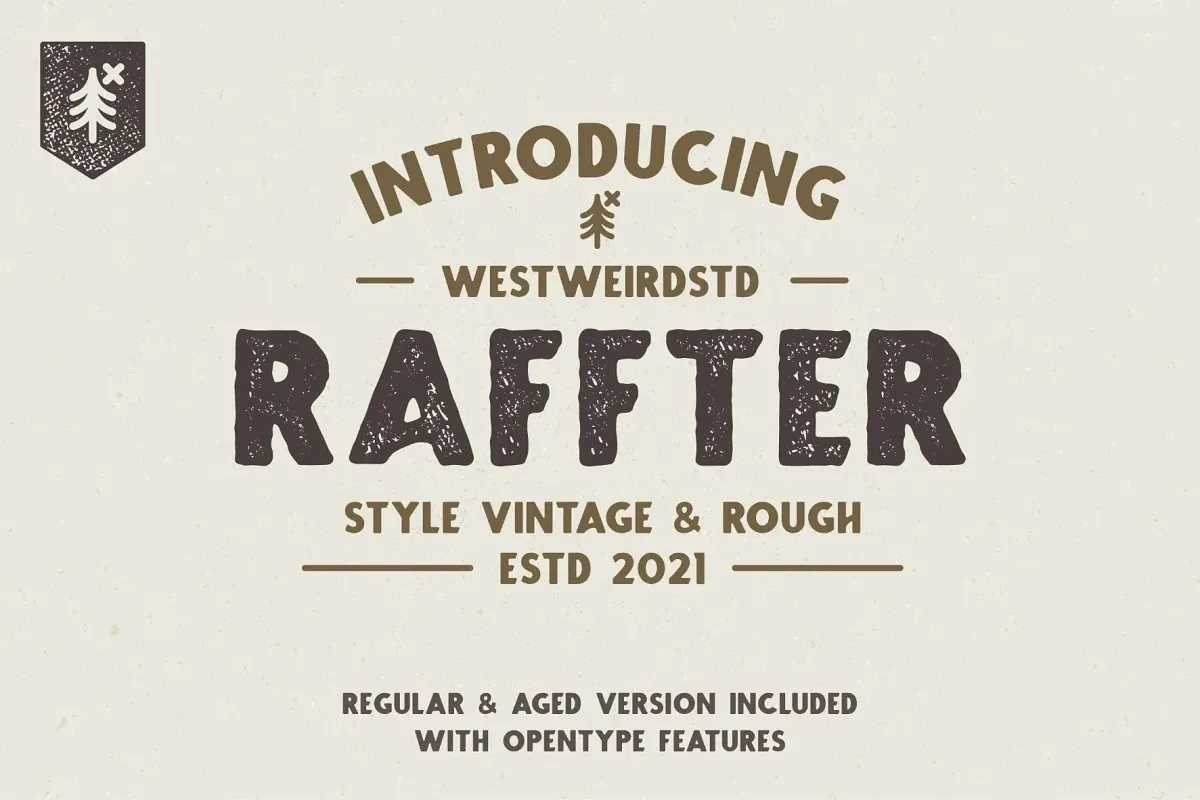
A Raffter Font é uma escolha perfeita para quem busca adicionar um toque único e vintage a seu design. Sua aparência desenhada à mão em estilo sans serif, mas com um ar elegante, não deixa dúvidas sobre sua qualidade. Este font foi criado por West Weird e compartilhado no site 99designs, apresentando uma riqueza de detalhes que remetem a um tempo mais antigo. Com suas letras clássicas e fortes em tons antiquados, o Raffter Font oferece uma aparência que combina elementos de antiguidade, escolas antigas e café. Suas quatro variações tornam este font ainda mais versátil, adequado para aplicações em temas que remetem a antigos estilos, cafés ou qualquer outro estilo vintage. Essa font é perfeita para os designers buscando adicionar uma atmosfera nostálgica e autêntica aos seus projetos. Seja em logotipos, títulos de filmes, selos, rótulos de bebidas ou qualquer outra forma de design que valorize a memória do passado, o Raffter Font pode ser sua escolha ideal.